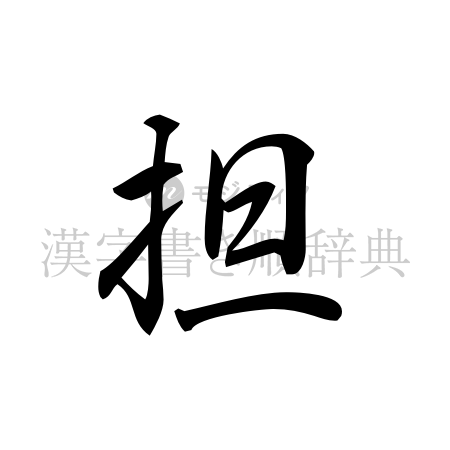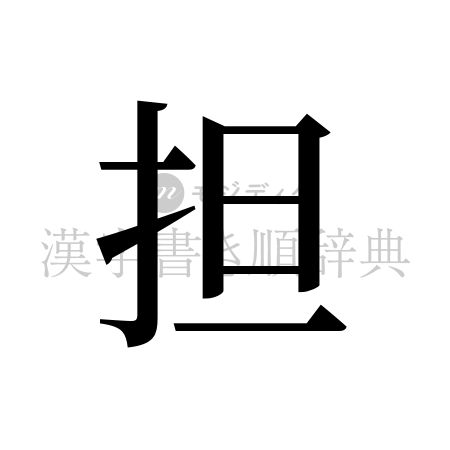
漢字「担」(てへんに旦)の書き順・読み方・意味・部首・画数
「担」の意味
- 肩にかつぐ。
- 責任を負う。
- 役割を引き受ける。
- 負担する。
- 支える。
「担」の意味の英訳
漢字は1文字で多様な意味を持ちますが、「担」を英語で表す場合、一般的には shouldering, carry, raise, bear などがあります。
「担」の成り立ち・由来
| 構造 | 意符扌(手)+音符詹(旧字体「擔」) |
旧字体は「擔」で、意符の「扌(手)」と音符の「詹(せん・たん)」から成る形声文字です。手でものを持ち上げ、肩にかつぐ動作を表し、そこから「になう」「責任を負う」の意味が生まれました。新字体では複雑な音符「詹」が「旦」に置き換えられ、「担」の形になりました。「旦」は朝日が地平線の上に昇るさまを表す字ですが、ここではもっぱら字画を簡略化するために用いられており、本来の意味とは直接の関わりはありません。1946年の当用漢字表で新字体が採用されました。
- 担架 - たんか
- 病人・負傷者などを乗せて運ぶ道具。普通、二本の長い棒の間に布を張ったもの。
- 担当 - たんとう
- 受け持ってその事に当たること。引き受けること。
- 分担 - ぶんたん
- 仕事・責任・費用などを分けて受け持つこと。分けて負担すること。